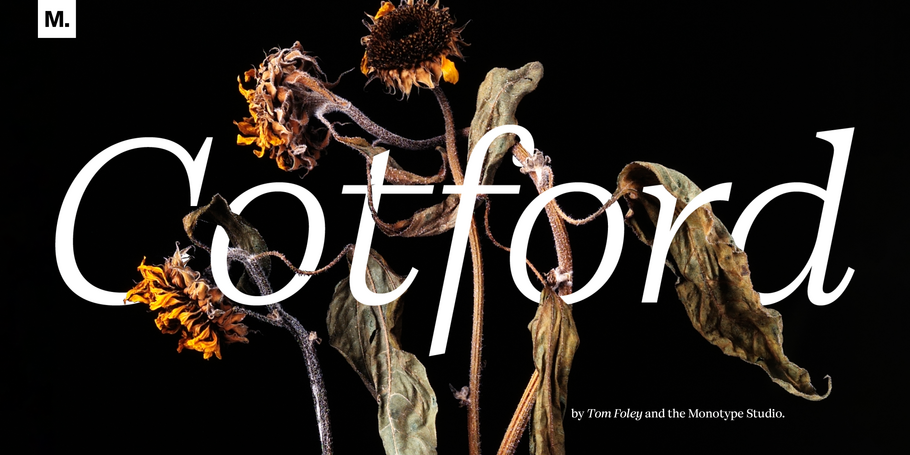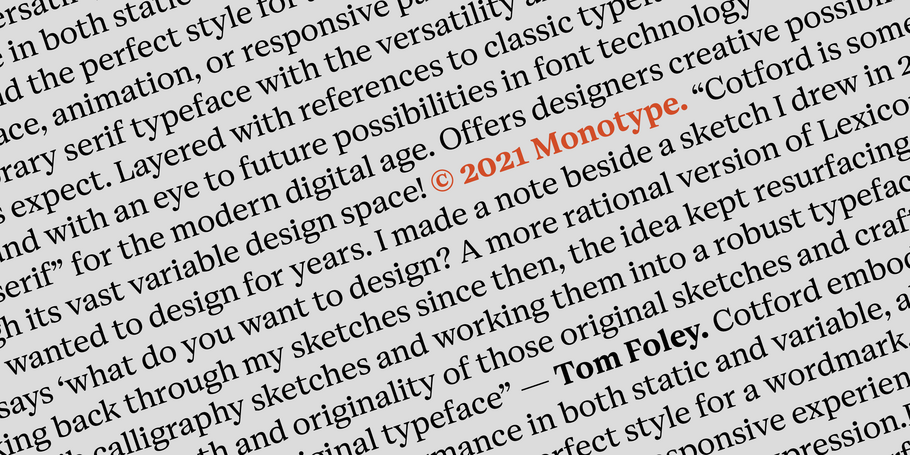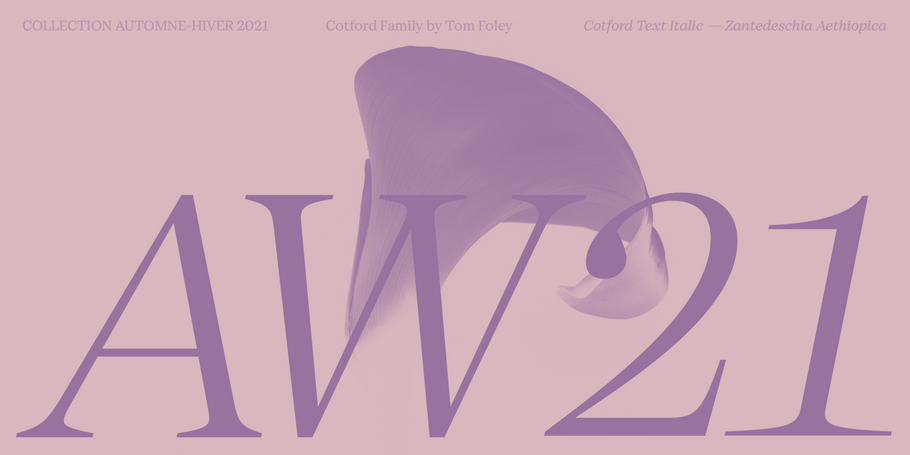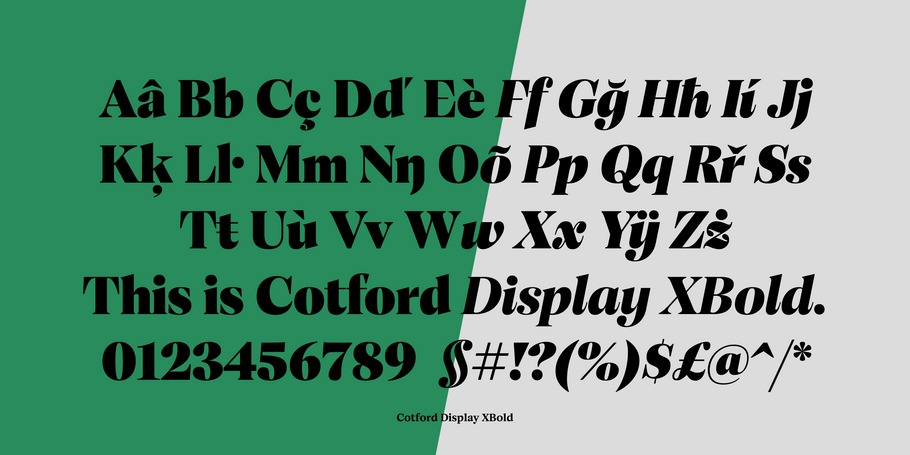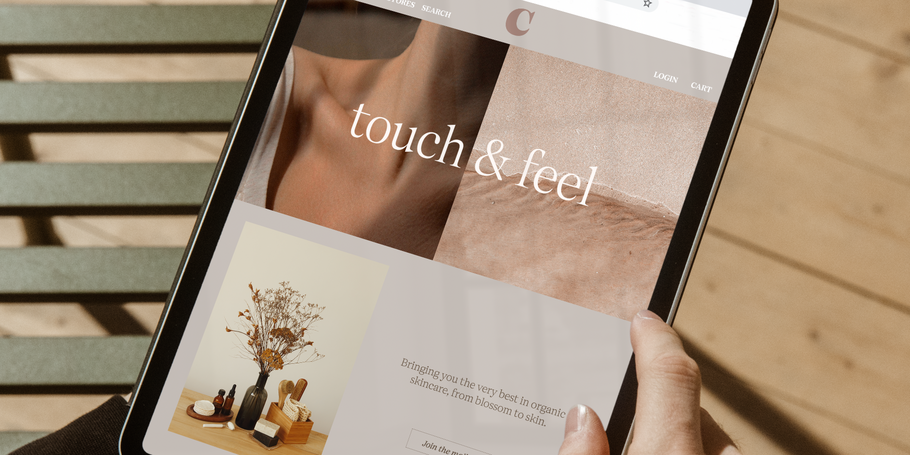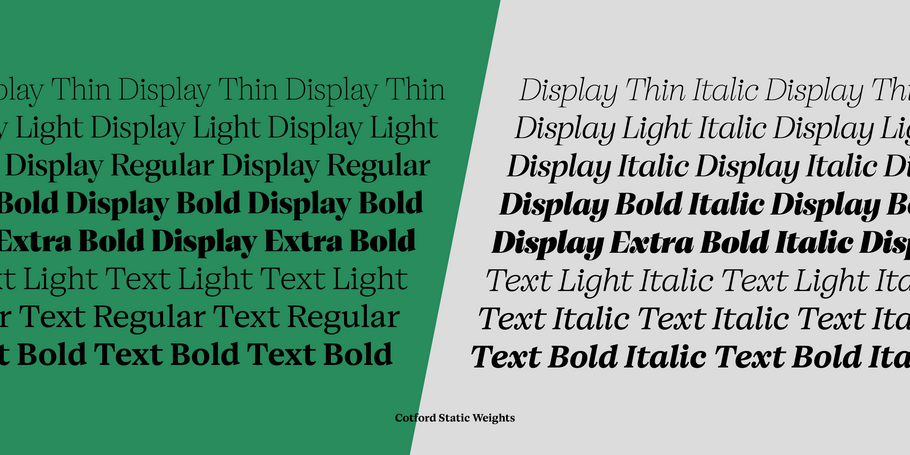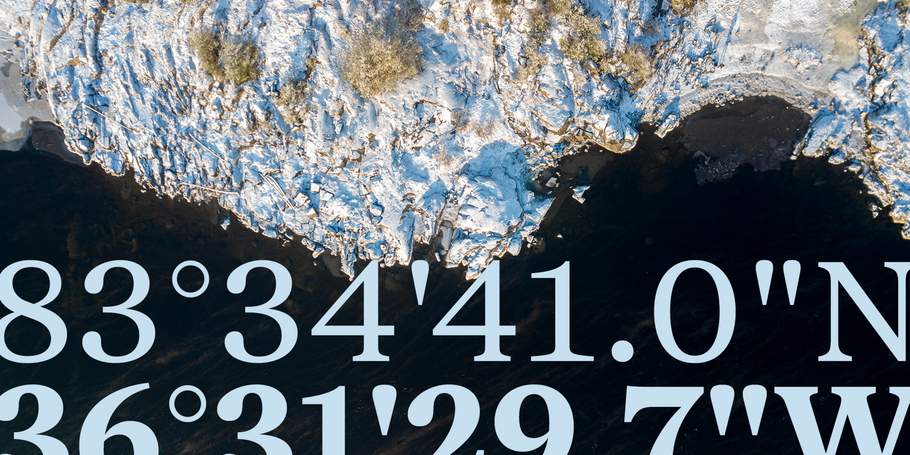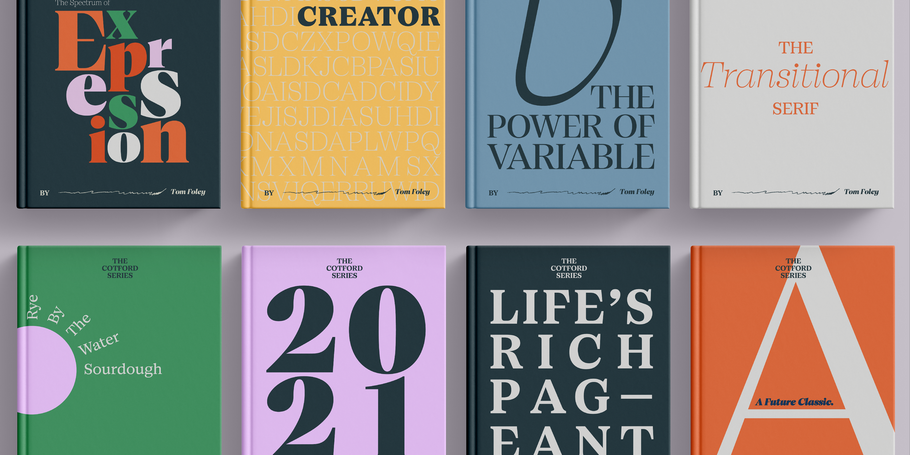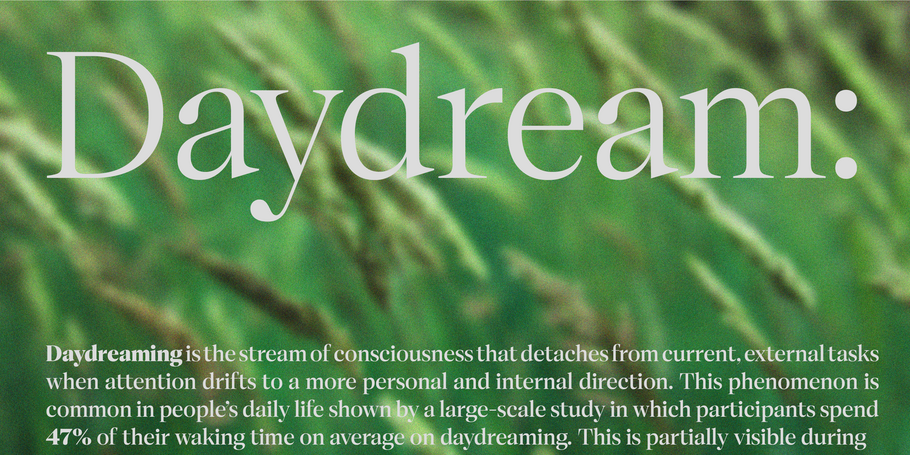
Cotford
Vous emmène partout.
Dynamique, adaptable et surprenante – Cotford est une famille de serifs décontractés qui va des graisses thin délicates aux bold audacieuses. Elle s’impose sur chaque page et écran avec une assurance et un charme vintage. Fonte variable, elle offre aux designers d’infinies nuances et autres secrets bien gardés.
Nouveauté du Studio Monotype, Cotford est une police serif contemporaine élaborée par le directeur de la création typographique Tom Foley. Dynamique, adaptable et surprenante, Cotford est une famille de serifs décontractés qui va des graisses thin délicates et souples comme les tiges des fleurs, aux bold audacieuses qui s’imposent avec une assurance et un charme vintage sur chaque page et écran. En tant que police variable, elle offre aux designers des explorations et ajustements infinis, dévoilant ses nombreux tons visuels et autres secrets bien gardés.
Foley a opté pour la création d’une fonte serif contemporaine expressive, qui offre toute la polyvalence et la robustesse attendue par les designers d’aujourd’hui. Variable, elle révèle un spectre d’expression visuelle élargi qui permet aux designers d’obtenir la graisse, le contraste et la taille optique parfaite pour chaque projet. Les graisses statiques de Cotford suivent, quant à elles, un modèle traditionnel de trois graisses de texte et cinq graisses d’affichage, ce qui en fait un choix sûr pour les marques qui cherchent une mise en œuvre simple.
Une serif pop pour l’ère numérique. Cotford vous emmène partout.
Tom Foley est directeur de la création typographique pour Monotype. Il dirige une équipe de designers typographiques pour la typothèque Monotype et les marques d’entreprise. Les mots et les lettres coulent dans les veines de Tom – son arrière-grand-père était issu d’une famille de tailleurs de pierre spécialisé dans la sculpture de lettres, et son oncle était peintre d’enseignes.